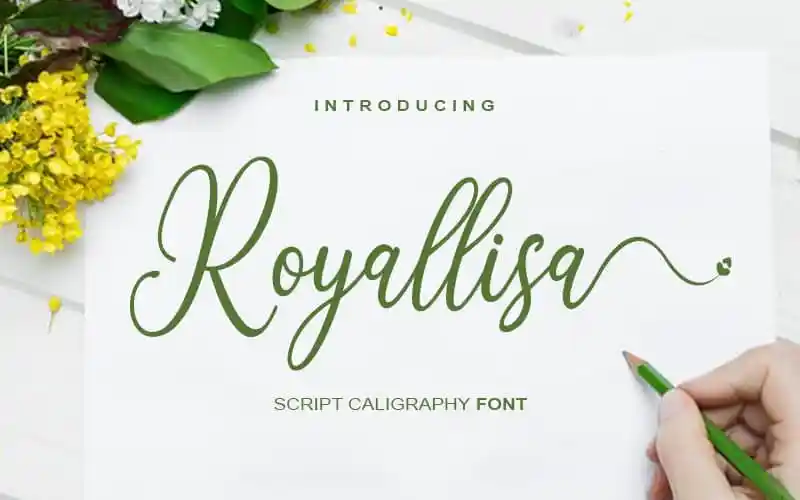
Royallisa Calligraphy Font – Download Grátis
Royallisa Calligraphy Font é uma excelente opção para quem procura uma fonte escrita a mão que preserva seus encantos tradicionais de calligrafia, ao mesmo tempo em que adquirem um toque contemporâneo e moderno. Com seu caráter versátil, essa fonte será particularmente apreciada por designers que buscam inspiração para conceitos criativos como cartões de visita e títulos para se unirem perfeitamente a materiais de decoração de escritório. Suas linhas elegantes e sutileza fazem do Royallisa Calligraphy Font uma escolha inteligente para qualquer projeto que valorize estilo e sofisticação, enquanto manterá seu design inovador e atual.